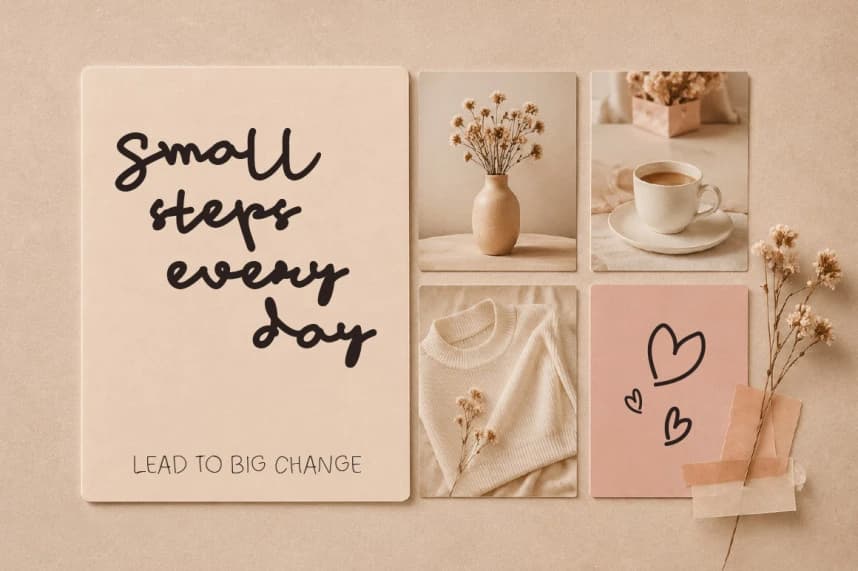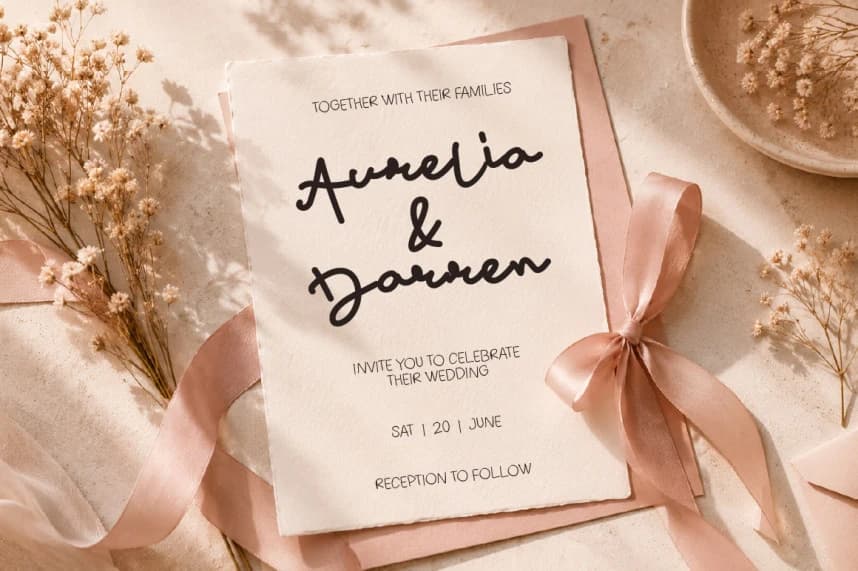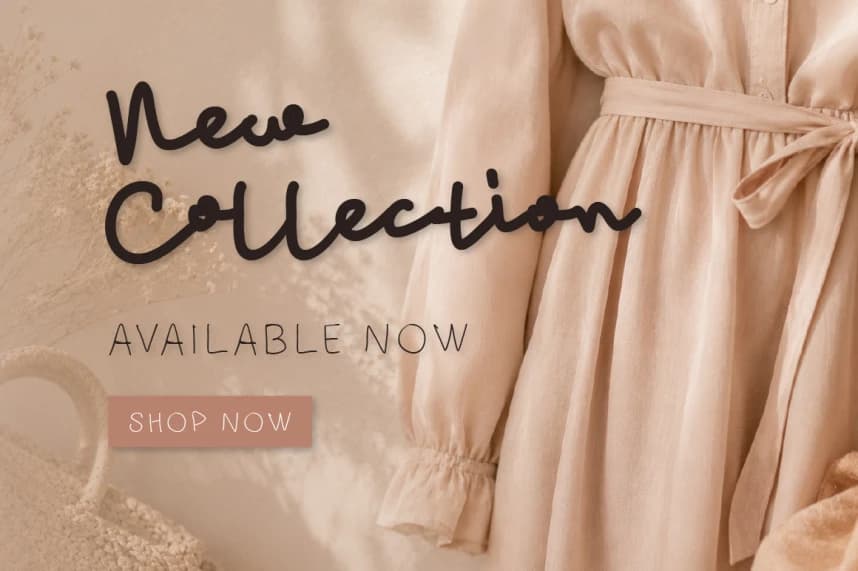
Elfariany Duo, ifadesi güçlü bir imza yazı stiliyle temiz bir monoline el yazısı sansını bir araya getiren modern bir el yazısı font ikilisidir. Sıcak, şık ve kişisel marka görselleri oluşturmak için tasarlandı; bu ikili zarafet ile gündelik samimiyet arasında mükemmel bir denge sunar.
Elfariany Duo, ifadeli bir imza yazı tipiyle temiz bir monoline el yazısı sansını bir araya getiren modern bir el yazısı font ikilisidir. Sıcak, şık ve kişisel marka görselleri yaratmak için tasarlanmış olan bu ikili, zarafet ile günlük otantiklik arasında mükemmel bir denge sunar.